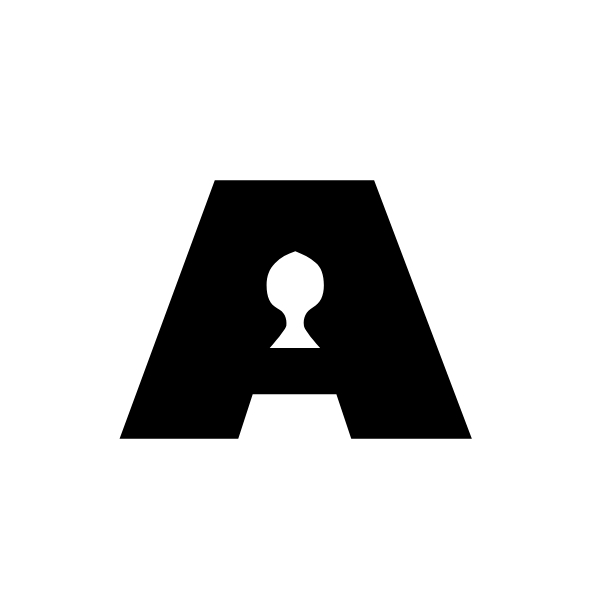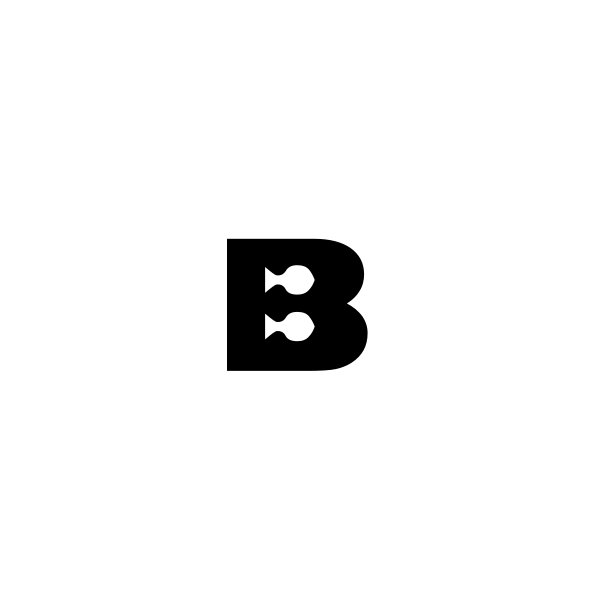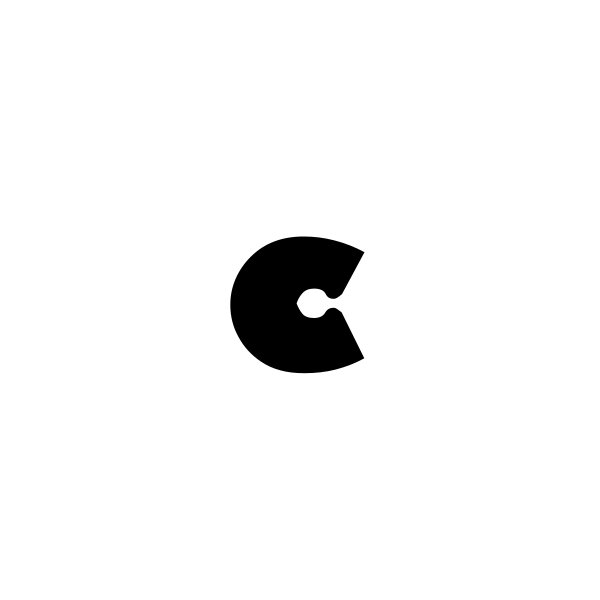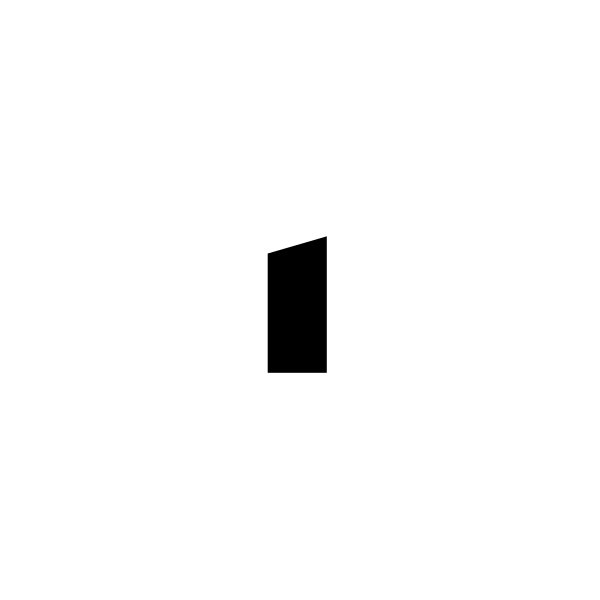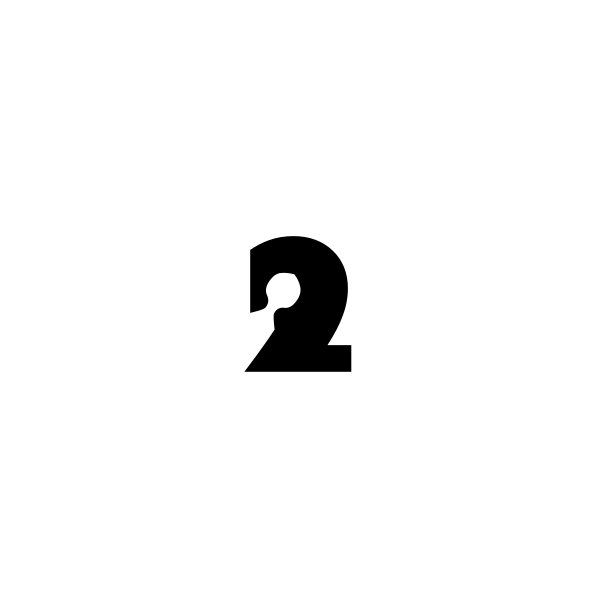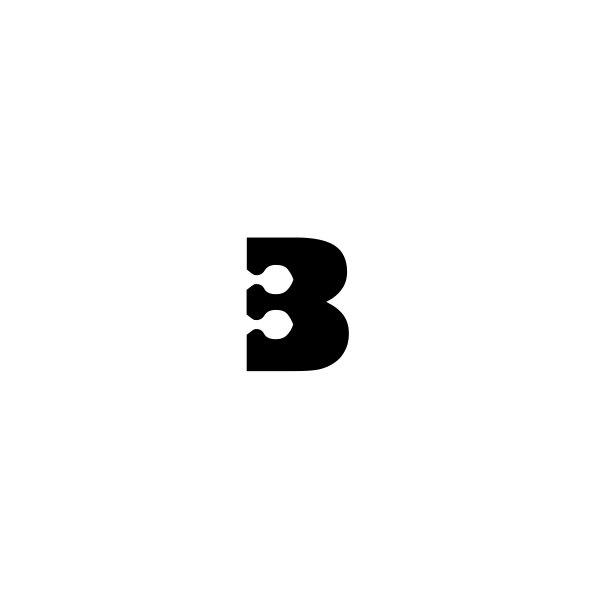
Lake Adventure Font ist eine verspielte, wasserinspirierte Schrift mit kräftigen, soliden Buchstabenformen und kleinen dekorativen Ausschnitten, die kleine Fische und Bewegung im Wasser darstellen. Der Stil wirkt fröhlich und auffällig und eignet sich besonders gut für Kinderprojekte, personalisierte Namen, Partydekorationen und kreative Basteldesigns. Durch die klare und stabile Form eignet sich die Schrift besonders für grössere Texte und auffällige Überschriften, bleibt dabei aber freundlich und verspielt im Gesamtbild.